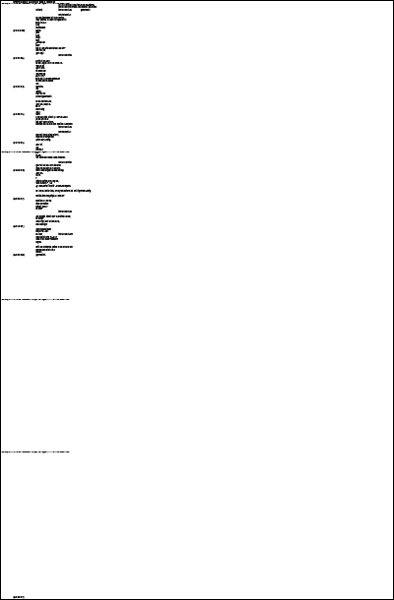
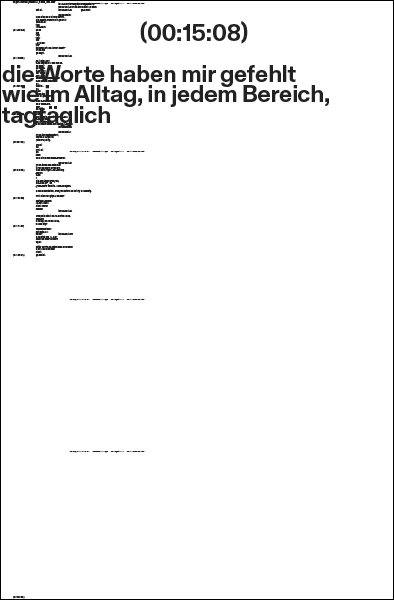
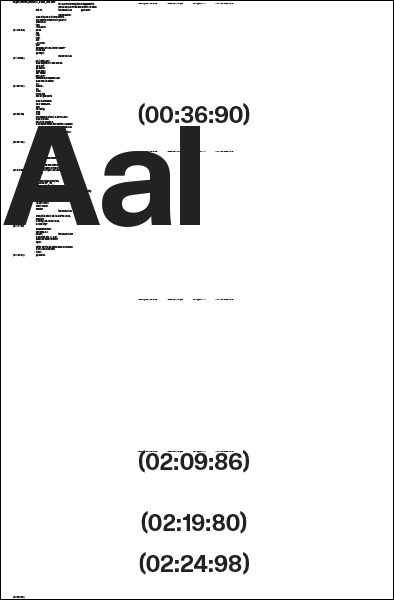
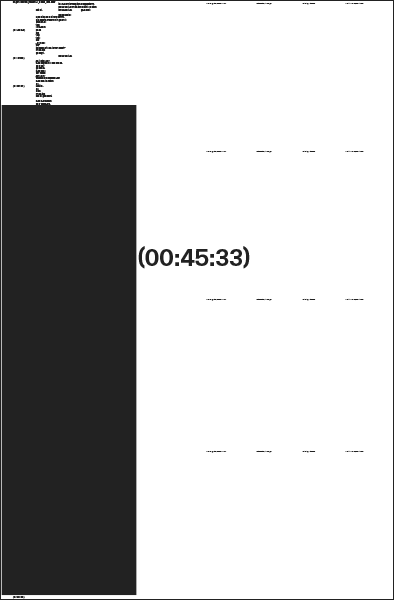
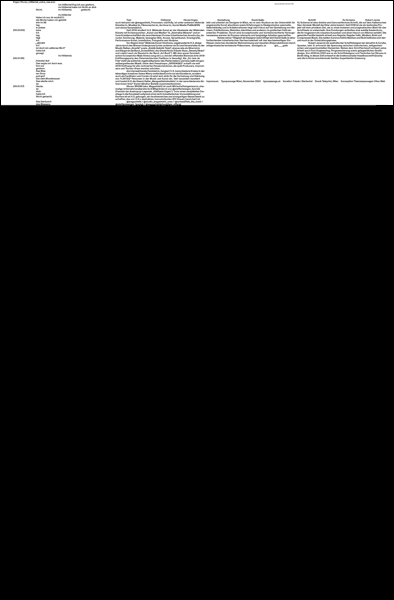
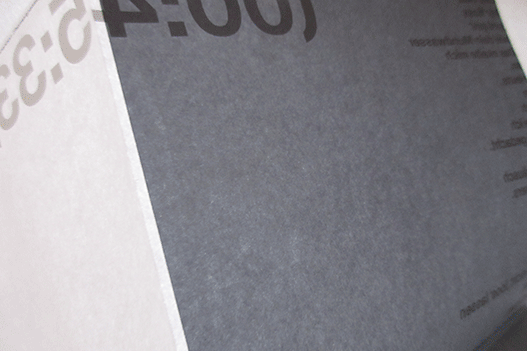
Typografie
RJ Schema by Robert Janes. RJ Schema ist eine direkte und klare serifenlose Schrift, die auf dem italienischen Neo-Grotesk-Modell der 60er Jahre basiert. Seit 2018 ist sie ein laufendes Projekt mit dem primären Ziel, sie zu einer lesbaren und pragmatischen Wahl fu?r den Schriftsatz zu entwickeln. Ihre Rundungen enthalten eine subtile Kastenform, die ihr insgesamt ein robustes Aussehen und einen Hauch von Wärme verleiht. Die gesamte Familie besteht aktuell aus Regular, Regular Italic, Medium, Bold und Compressed Black. Die beiden Kursivschnitte Medium und Bold befinden sich derzeit noch in der Entwicklungsphase. Robert Janes ist ein australischer Schriftdesigner der aktuell in A Coruña, Spanien, lebt. Er erforscht die Spannung zwischen historischen, zeitgenössischen und experimentellen Elementen. Neben dem Schriftentwurf umfasst seine Arbeit auch Font Engineering, Programmierung sowie gelegentliches Grafikdesign. Von 2018 bis 2022 war er als Schriftdesigner und Techniker bei Dinamo in Berlin tätig. In dieser Zeit entwarf er die breitenvariable Headlineschrift Gravity und die in Kürze erscheinende Serifen-Superfamilie Gramercy.